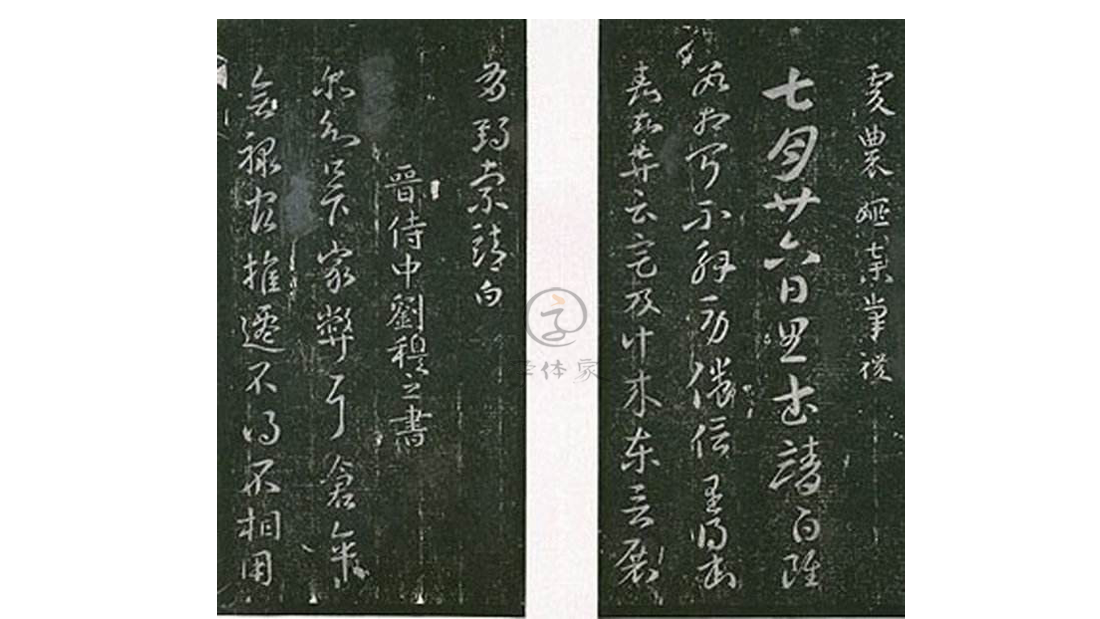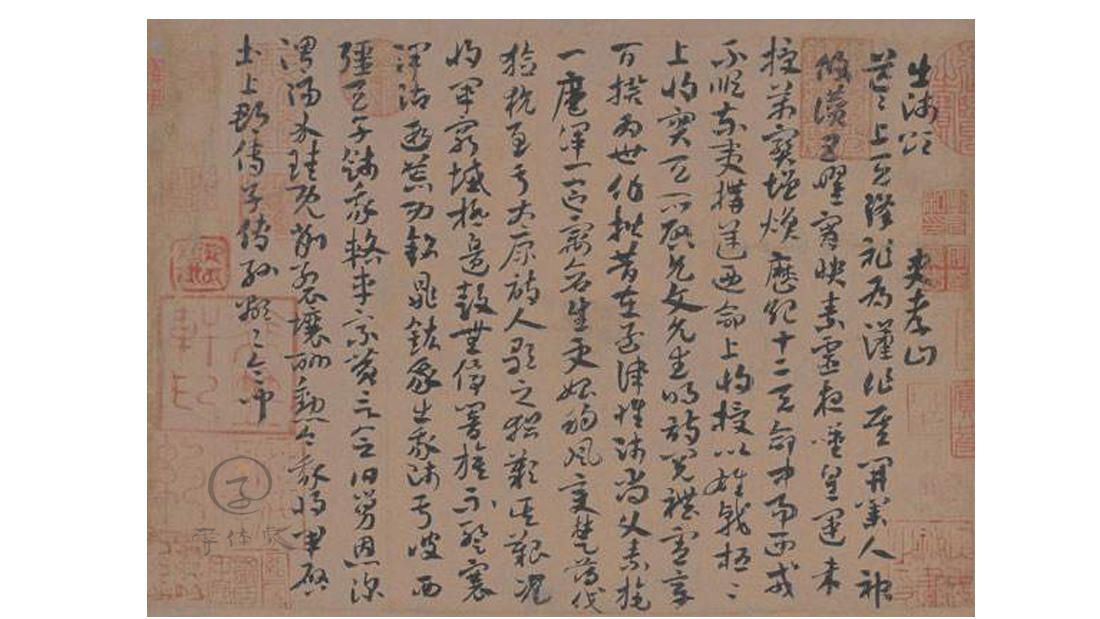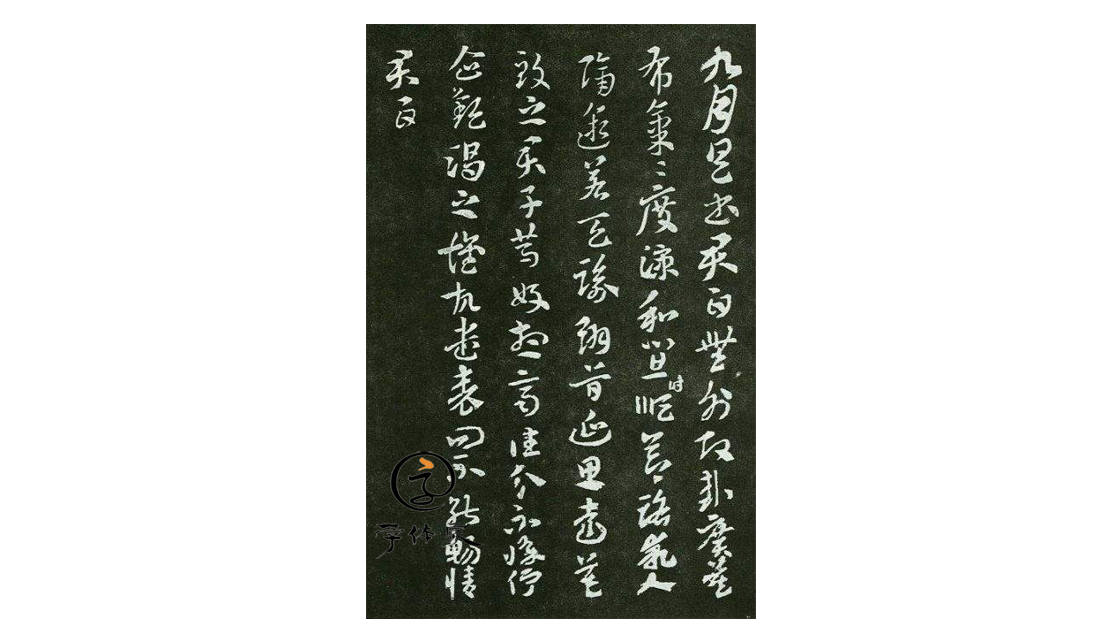
索靖|在中国文化史上是位有重要影响的人
索靖(239年-303年),字幼安。敦煌郡龙勒县(今甘肃敦煌)人。西晋将领、著名书法家,敦煌五龙之一。索靖出身世宦家族,历任州别驾、驸马都尉、尚书郎、雁门太守等职。晋惠帝时封关内侯,以荡寇将军之职平定西羌叛乱。赵王司马伦篡位时,索靖响应三王举义有功,累官后将军。河间王司马颙进攻洛阳时,索靖率雍、秦、凉义兵大破其军,却因战斗致伤而逝世,年六十五。累赠司空、安乐亭侯,谥号“庄”。
索靖善章草,传东汉张芝之法,其书险峻坚劲。其章草书,自名“银钩虿尾”,时人称“瓘得伯英之筋,靖得伯英之肉”。索靖的章草自成一家,被张怀瓘评道“有若山形中裂,水势悬流,云岭孤松,冰河危石,其坚劲则古今不逮。”著有《草书状》等。
索靖流传后世的书法作品有《出师颂》、《月仪帖》、《急就章》等。宋代著名的《淳化阁帖》也收集了索靖的墨迹《载妖帖》八行、《七月帖》四行。他的书法对后世影响很大。唐代书法家欧阳询平生最重法度,不肯轻易推许古人。一次,他路见索靖书写的碑石后,竟卧于碑下,朝夕摩掌,不忍离去。
索靖的书法,浓浅得度,内涵朴厚,古朴如汉隶,转折似今草,气势是相当雄厚的,历来被书法家称为上乘。梁武帝萧衍称誉他的字“遒劲而峻险。遒劲处如飘风忽举,鸷鸟乍飞;峻险处如雪岭孤松,冰河危石”。黄山谷也称道他书法为“笺短意长,诚不可及”。有人把索靖的字与张芝的字作了比较,认为:“精熟至极,索不及张芝;妙有余姿,张不及索靖”。两位大师的书法是各见所长。
索靖在中国文化史上是位有重要影响的人。他是东汉著名书法家张芝姊之孙,书法上受张芝影响很深。以善写草书知名于世,尤精章草(章草是隶书草化后的书体)。晋武帝时,他和另一大书法家卫瓘同在尚书台供职。卫瓘为尚书令,索靖为尚书郎。由于二人在书法艺术上独具风格,当时被人们誉为“一台二妙”。说他二人的书法与张芝有很深的师承关系。后人评价道:“瓘得伯英(张芝字)筋,靖得伯英肉”。